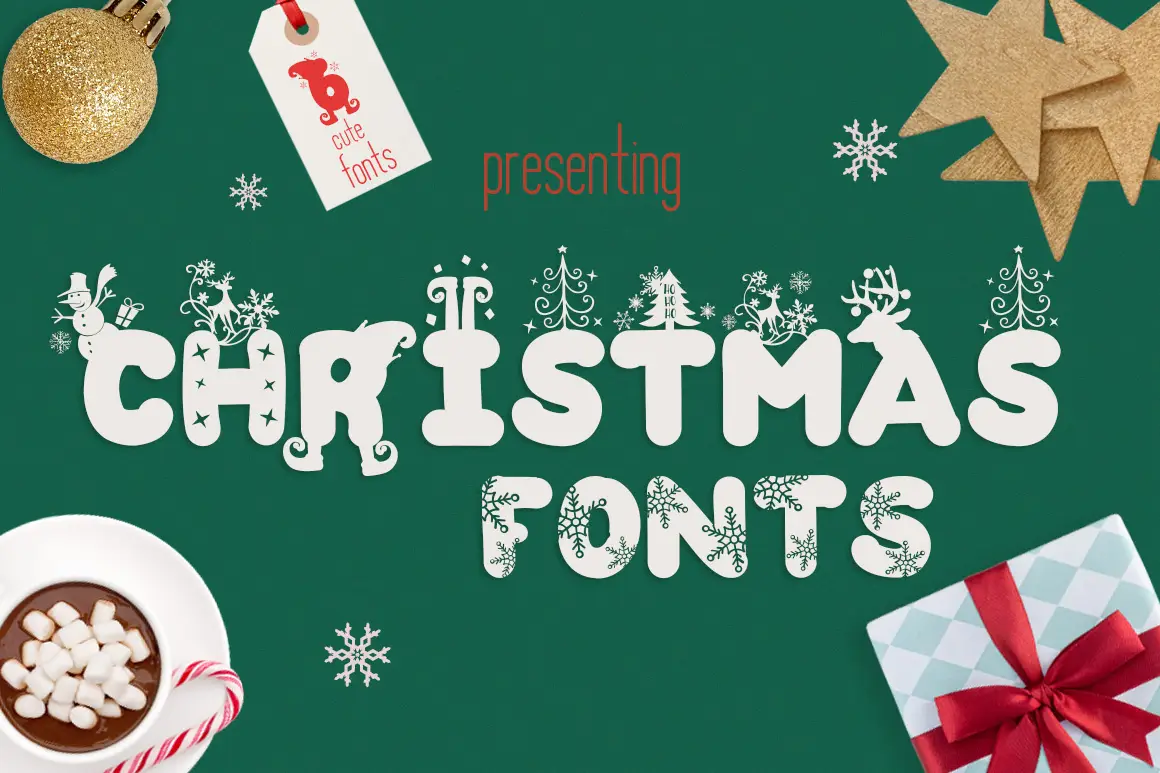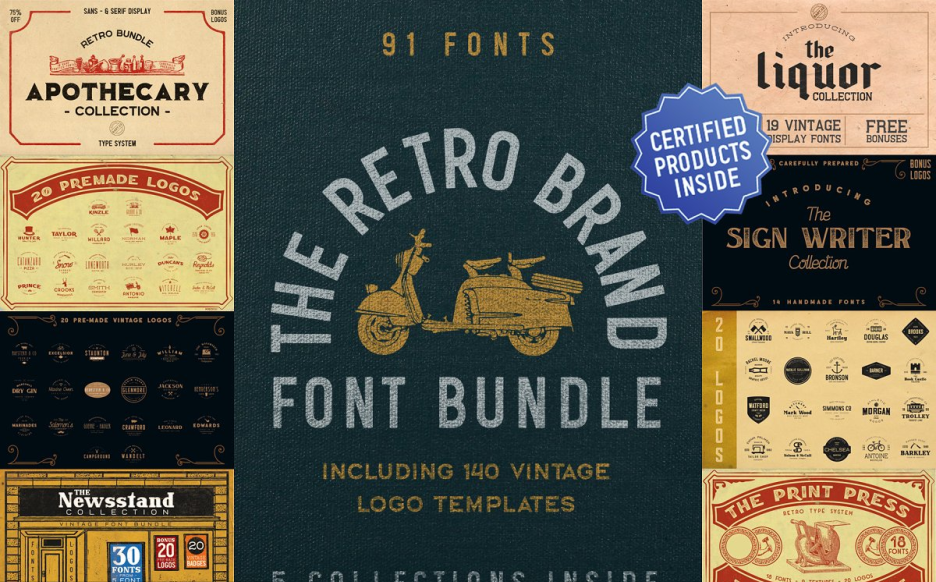
嘿,创意灵魂!👋 欢迎来到我们史诗级 Brushespack 收藏之旅的第150站。如果你和我一样是设计师、数字艺术家或字体爱好者,你一定知道合适的字体能成就一个项目,也能毁掉它。今天,我们将深入探索20个绝对令人惊艳的字体包,它们将为你的设计武器库注入超强动力!🚀✨
为什么要使用这些字体包?
别再一个个寻找完美的字体了。这些精选字体包旨在为您节省时间、金钱和创作烦恼。无论您是在设计复古标志、浪漫婚礼请柬还是惊悚万圣节传单,拥有海量优质字体库意味着您永远不会灵感枯竭。而且,它们都品质一流,可直接用于商业用途!💪🎨
Top 20 Brushespack 字体合集精选
复古供应字体包
用这款包含衬线、无衬线、手写体和展示字体的绝妙合集,释放您内心的复古情怀!非常适合品牌设计和复古海报。🌟
维多利亚风格装饰衬线字体包
为您的邀请函、标志和品牌设计增添一丝永恒优雅。这些精美的装饰衬线字体,尽显经典气质!🕰️✨
西部字体包 – 56款字体
哟嚯!🤠 这款包含56款独特字体的超大字体包将为你的设计带来狂野西部风情。从粗犷的衬线字体到优雅的手写体,是打造乡村风格项目的必备之选。
复古品牌字体合集 3590884 Vfx
复古品牌设计所需的一切尽在此处:手写体、无衬线体与展示字体,满满怀旧风情。你的Logo会感激不尽的!📺🎶
终极手工字体包 – 50款高级字体,价值超$
五十款高级字体打包在一起?当然要!从优雅手写体到醒目展示体,这是你手工艺创作的终极伴侣。🧵✂️
情人节甜蜜字体套装
用这组迷人的手写体、衬线体和无衬线字体合集,传递爱意💘。适合婚礼请柬、情书以及甜蜜品牌设计!
壮观字体合集 – 27合1字体包
27款独特字体,涵盖衬线体、无衬线体、手写体与装饰风格——这是一次满足所有设计需求的超值优惠!🎉🔥
终极字体包
名副其实:多种字重、OTF/TTF/WOFF格式,风格从优雅衬线体到现代无衬线体一应俱全。名副其实!🏆
神奇迷你字体套装
别被“迷你”二字骗了——这个套装包含多款 versatile 的衬线、无衬线和手写字体,完美适用于任何项目!🎁✨
特别收藏字体套装
精心挑选的衬线、无衬线、手写和展示字体合集,提供OTF/TTF/WOFF格式。真正独特,与您的设计相得益彰!🌟💎
特制现代手写字体合集 – 59款高级字体
59个高级手写字体,优雅流畅且富有现代感。这是为现代设计师量身打造的终极手写字体合集!🖋️🌈
威士忌字体合集
质朴、迷人,且充满个性——正如一杯上好的威士忌!🥃 适合酒吧菜单、手工艺品牌及复古风格的设计。
手写字体包 – 13款手写字体合集
用 13 款独特的 hand-written 手写字体,增添那份亲切的人情味。非常适合笔记、邀请函和温馨的品牌设计!📝💛
超级特别字体包 – 65 款高级字体,价值 $
65款高级字体,涵盖衬线、无衬线、手写和显示风格。这是专为严肃设计师打造的超级特惠!🚀💰
圣诞字体包
感受节日气氛!🎄 这个节日合集包含优雅的手写体和粗体展示字体,适合您所有的季节性项目。
超级专属字体合集
另一个令人难以置信的字体包,包含衬线、无衬线、手写和展示风格,满足所有排版需求。双倍庆祝!🎊
盐与胡椒字体包 – 第1卷
手写体、衬线体和无衬线字体的完美平衡,为你的设计项目带来恰到好处的调味!🧂🌶️
浪漫手写字体合集 – 46款字体
46款精美手写字体,为您的品牌、标志和邀请函增添优雅与魅力。爱在细节中!💕🖋️
优雅装饰手写字体套装
高雅与艺术的完美融合!这套流畅的手写体与华丽装饰字体系列,专为高端品牌和奢华项目打造。👑✨
万圣节字体合集
恐怖但有趣!🎃 这款万圣节字体包含常规、粗体和斜体样式,并带有独特的主题字符,非常适合传单和派对邀请函!